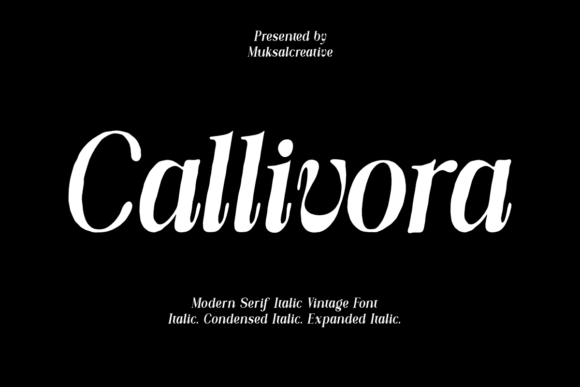
Callivora Italic
Si buscas recursos de alta calidad como Callivora Italic, este paquete premium es una opción fantástica para tus proyectos creativos.
Ya sea que estés creando productos POD (impresión bajo demanda), invitaciones de boda o gráficos para redes sociales, Callivora Italic es una opción ideal.